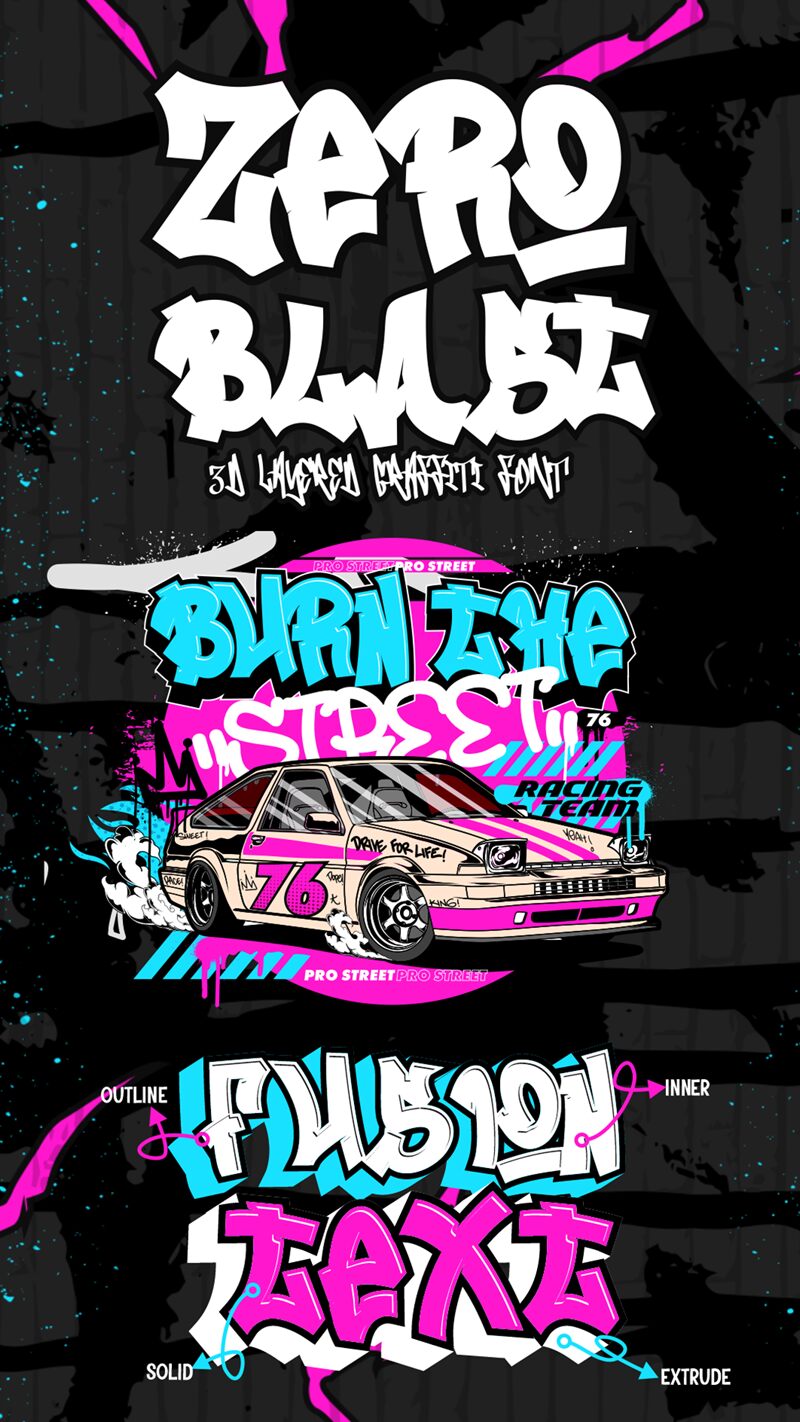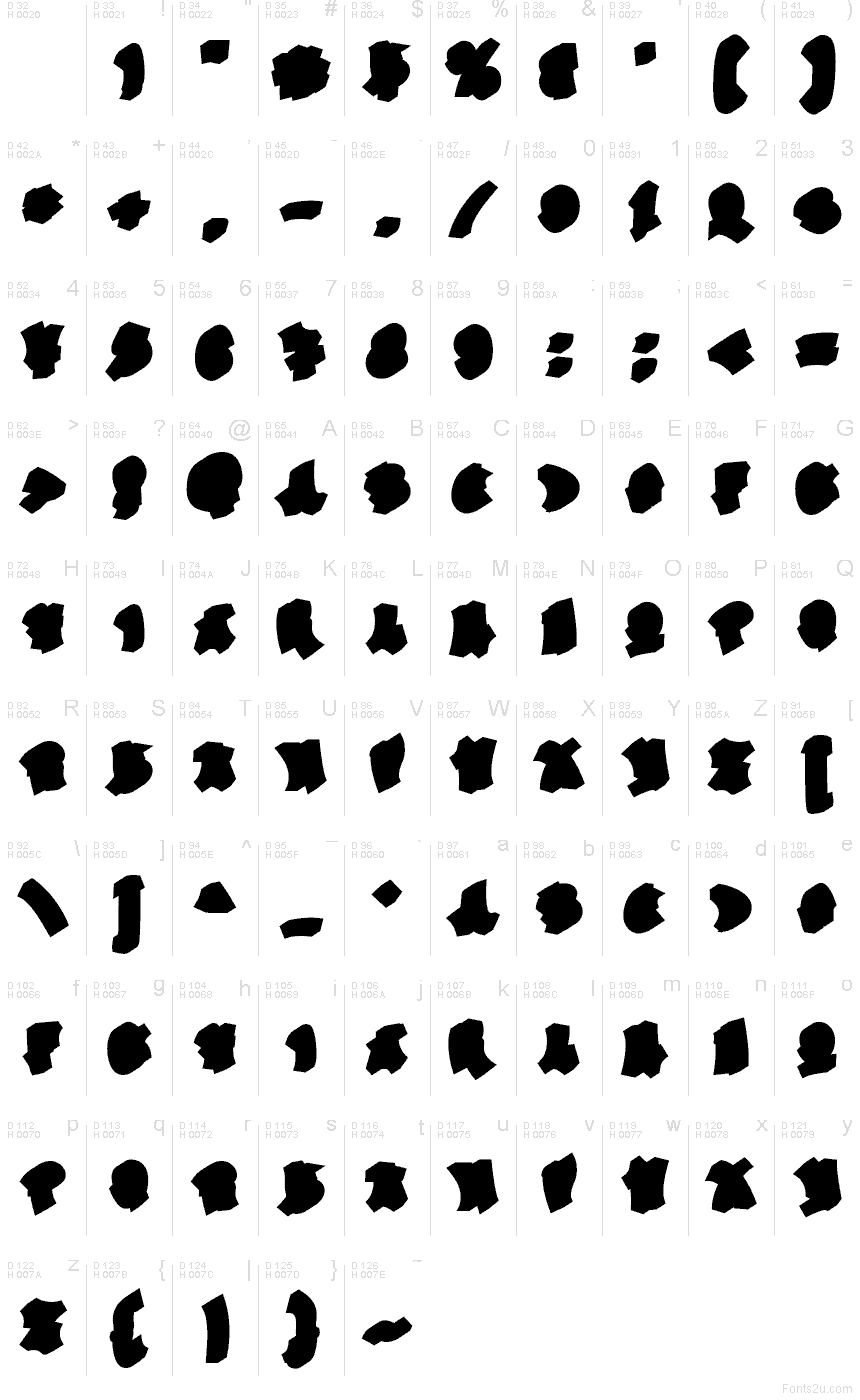
Zero Blast Extrude di Muhammad Panji Ramdhani (Sipanji x Figuree) è un font graffiti gratuito che sprigiona l'energia cruda di una bomboletta spray. Grazie alla sua audace ombra estrusa, ogni parola sembra staccarsi dalla parete. Le forme sono compatte e dai bordi irregolari, dando ai tuoi titoli un ritmo urbano e graffiante, mentre la silhouette spessa garantisce un impatto visivo immediato e leggibile.
Zero Blast Extrude è perfetto per loghi streetwear, poster da skate, flyer musicali, miniature YouTube, titoli di giochi, adesivi e campagne social incisive. Usa questo font gratuito in grandi dimensioni per far respirare l'estrusione e abbinalo a un carattere sans-serif geometrico per il testo principale, così da tenere sotto controllo il caos. È la scelta naturale quando cerchi un impatto potente senza bisogno di effetti aggiuntivi: sono già inclusi nel design.